マンガでわかる「日本絵画」のテーマ
誠文堂新光社は、2019年2月18日(月)に、矢島新氏監修、唐木みゆ氏担当『マンガでわかる「日本絵画」のテーマ』を発売した。
マンガでわかる「日本絵画」のテーマの表紙のフォントに「古籍黒檀」が採用
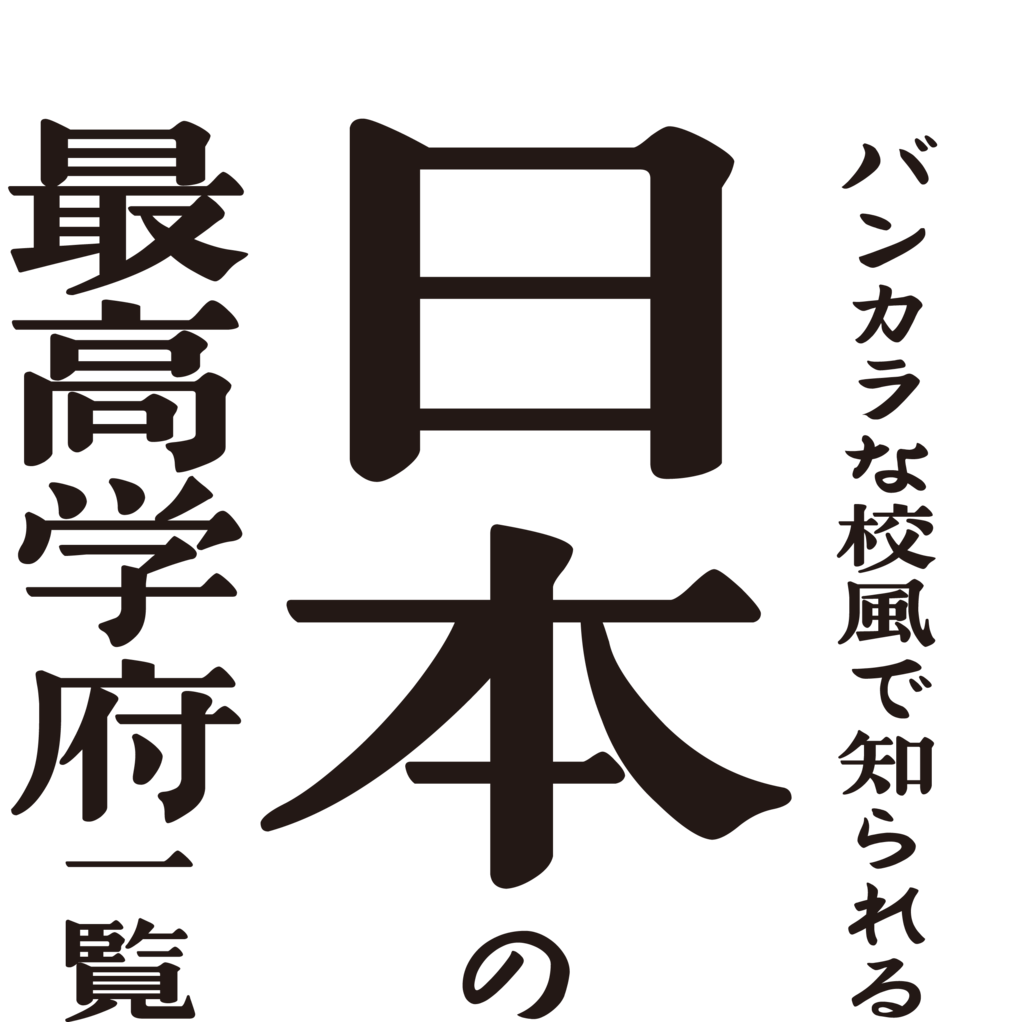
マンガでわかる「日本絵画」のテーマの表紙のタイトルやテキスト部分のフォントにダイナフォントのグッドデザイン賞受賞書体である古籍書体シリーズの「古籍黒檀」が使用されている。
古籍黒檀
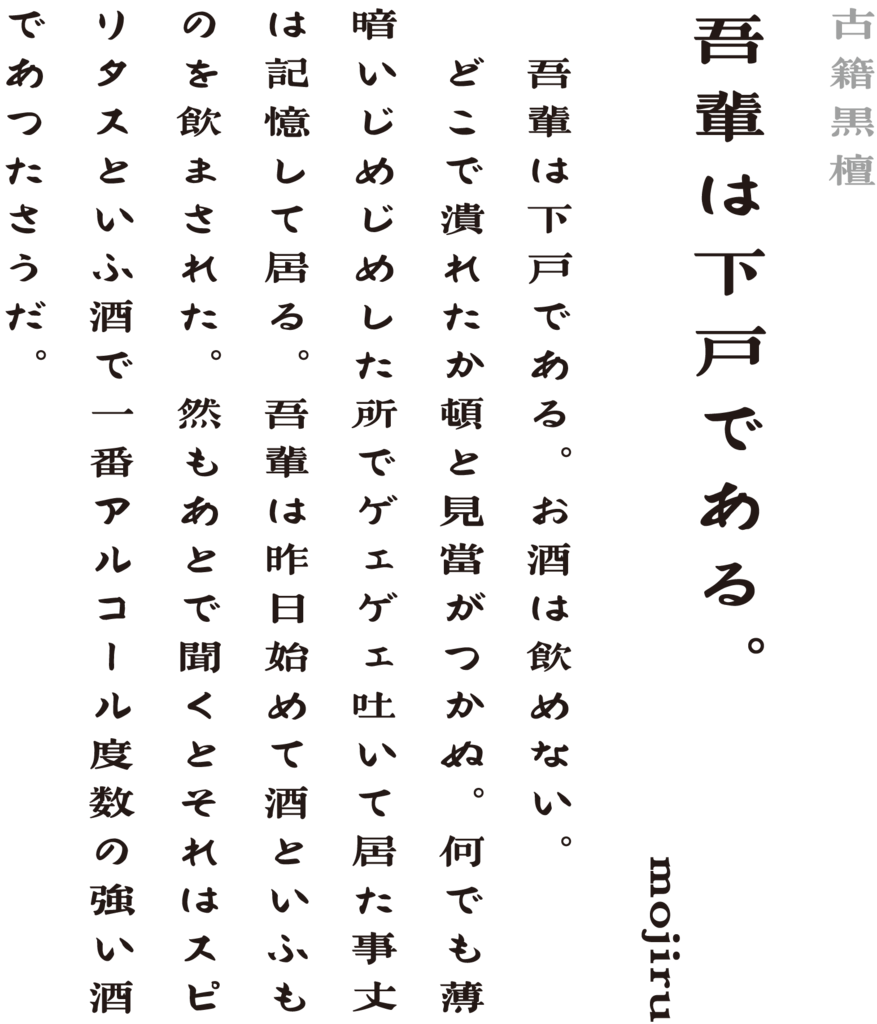
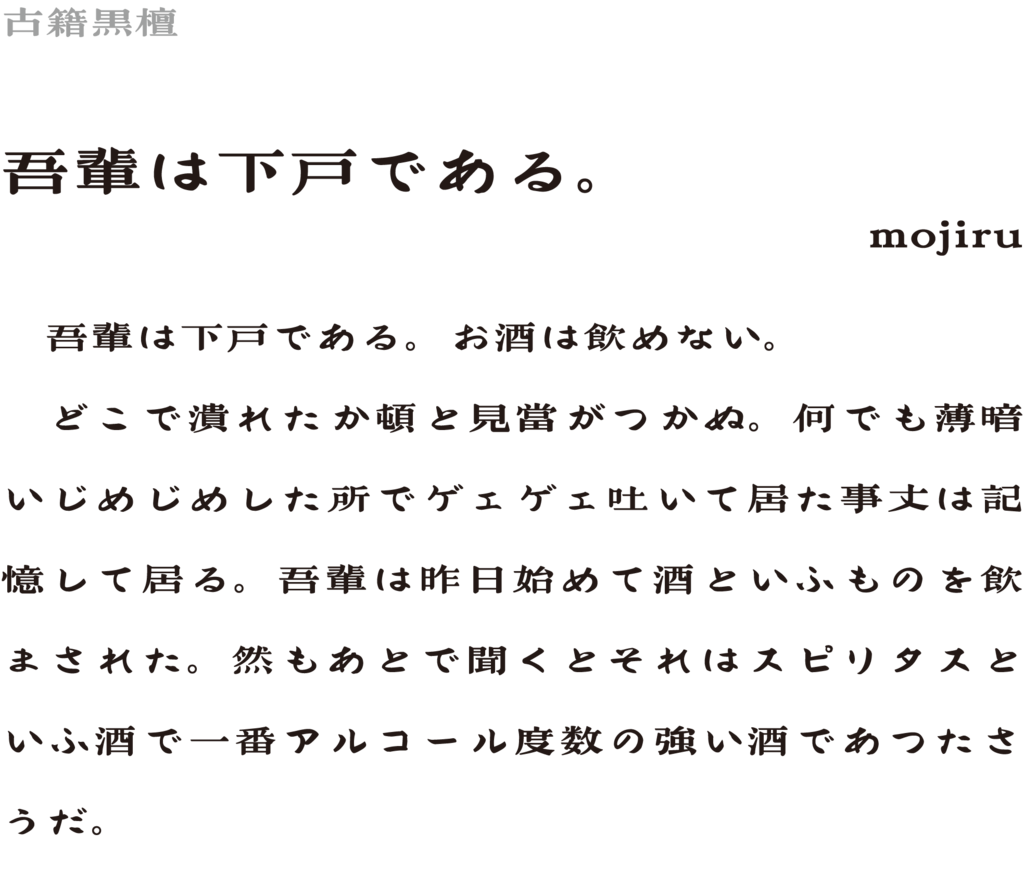
中国の古籍「范伯子集」の書帖をもとに開発された書体。「范伯子集」の文字は扁平な字形に重厚なストロークが特徴で、転折が力強く彫刻の質感のような雰囲気が溢れている。